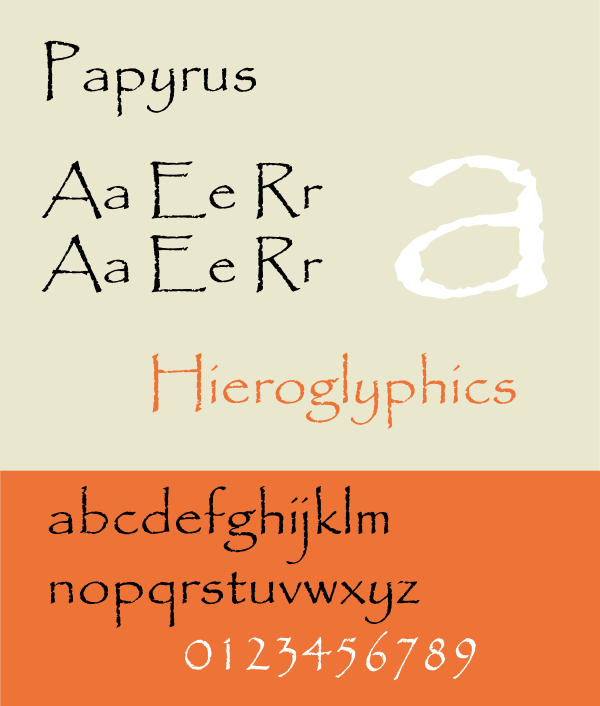
Papyrus (шрифт)
Papyrus — шрифт, разработанный графическим дизайнером, иллюстратором и веб-дизайнером Крисом Костелло. Был создан в 1982 году и впоследствии приобретён компанией Линотип. Имеет ряд характеристик, отличающих его от других шрифтов, в том числе грубые края, неправильные изгибы и высокие горизонтальные штрихи в заглавных буквах.
| Стиль | рукописный шрифт |
| Дата создания | 1982 |
| Дизайнер | Крис Костелло |
| Словолитня | Letraset[d] |
История
Костелло создал шрифт в 1982 году, когда ему было 23 года, вскоре после окончания колледжа. В то время он изучал Библию и пытался представить, как выглядел бы письменный шрифт в библейские времена на Ближнем Востоке[1]. Он рисовал шрифт вручную каллиграфической ручкой на текстурированной бумаге в течение шести месяцев. В качестве основной цели Костелло обозначил создание шрифта, по которому можно было представить, как выглядел бы текст на английском языке, написанный на папирусе 2 000 лет назад[2]. Спустя год создатель выпустил шрифт совместно с компанией Letraset. Костелло продал права на шрифт фирме Линотип за 750 долларов (что эквивалентно 2100 долларам в 2021 году) и заявляет, что по состоянию на 2017 год он по-прежнему получает «очень низкие» лицензионные платежи, несмотря на то, что с 2000 года он включён во все персональные компьютеры, использующие операционную систему Mac или Microsoft[1]. Текущий владелец прав на шрифт, компания International Typeface Corporation (Линотип), описывает его как «необычный латинский шрифт, который эффективно сочетает в себе элегантность традиционной римской формы букв с ручным видом высококвалифицированной каллиграфии[3]. По словам самого создателя, он не предполагал, что шрифт будет использоваться везде. Как утверждает Костелло, «он слишком часто используется»[4].
Использование
Шрифт используется во многих программах для платформы Windows[6]. В платформу Mac шрифт был включён в 2003 году, начиная с версии 10.3 Panther[7].
Критика и использование в культуре
Шрифт Papyrus часто критикуют за повсеместное распространение в сфера дизайна, особенно, когда он используется в ситуациях, для которых он не предназначался. В этом его критика напоминает критику шрифта Comic Sans[8]. В 2008 году был создан блог под названием «Papyrus Watch» для документирования повсеместного распространения и примеров неправильного использования шрифта[9].
Шрифт использовался для титров телевизионных сериалов Медиум и Эврика. В фильме Джеймса Кэмерона «Аватар» этот шрифт используется в названии и субтитрах[10]. Его использование в фильме было подчёркнуто в скетче телепердачи «Saturday Night Live» с участием Райана Гослинга[11]. Гослинг также упомянул, что шрифт широко используется в товарах под брендом Shakira, а также в кальянных барах и чайных компаниях[12].
В честь шрифта Papyrus в 2015 году Тоби Фоксом был назван персонаж Папирус в созданной им ролевой компьютерной игре Undertale. В диалогах в репликах персонажа всегда используется этот шрифт[13].